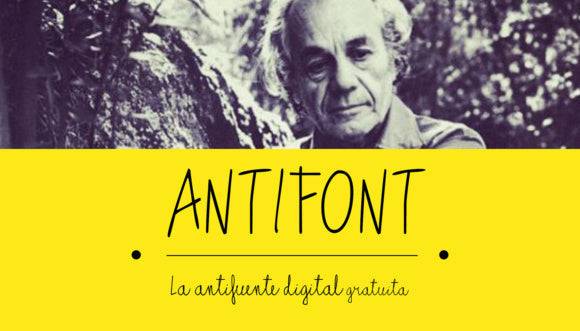
Fonte Anti para Títulos, Cartazes e Projetos de Identidade Visual
Esta lista inclui a fonte Anti Font, uma tipografia ousada da categoria de entidades de fontes, projetada para alta visibilidade em títulos e contextos de marca. Seus ângulos acentuados e traços grossos conferem um tom assertivo, ideal para projetos criativos que buscam uma declaração impactante.
De cartazes de shows a identidade visual arrojada para roupas, a Anti Font permite que os designers ultrapassem os limites da comunicação visual. Ela tem um desempenho excepcional tanto em ambientes impressos quanto digitais, onde uma forte presença tipográfica é necessária.
Para quem é indicado?
- Estrategistas de marca e designers gráficos
- Artistas de cartazes e criativos de layout
- Profissionais de marketing musical e designers de entretenimento
- Criadores de produtos de streetwear e estilo de vida
- Educadores criando materiais visuais arrojados
O que você pode fazer
- Cartazes, panfletos e banners para eventos
- Logotipos e marcas de identidade visual
- Capas de álbuns, adesivos e fanzines.
- Etiquetas de roupas e sinalização de lojas
- Impressões personalizadas, expositores de arte e embalagens.
Por que você vai adorar
- Estilo marcante para projetos com foco no visual.
- Ideal para branding e design de grande formato.
- Apresenta uma presença tipográfica marcante.
| Recurso | Fonte Anti | Fonte Genérica A | Fonte Genérica B |
| Estilo de design | Ousado, rebelde, de qualidade para exibição | Fonte neutra sem serifa | Serifa suave |
| Uso ideal | Títulos, identidade visual, produtos impressos | Texto básico do corpo | Títulos editoriais leves |